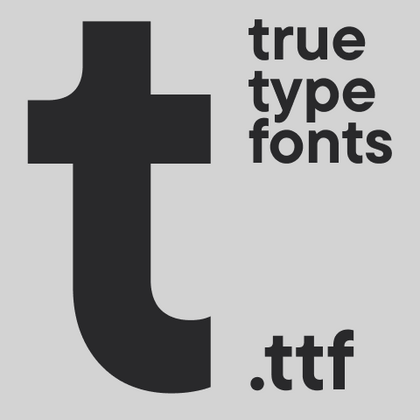
TTF шрифты
Когда нужна проверенная совместимость без сложных функций, TTF шрифты становятся идеальным решением. Каталог TypeType включает такие гарнитуры в разных стилях — от строгих рабочих вариантов до декоративных, с сохранением всех преимуществ формата: легкой установки и стабильного отображения в документах.
TT Polihaus — экспериментальный гротеск, который на первый взгляд кажется обычным, а затем разбирается на части, превращаясь в трафаретный узор.
TT Nooks Serif — акцидентная новостильная антиква с лёгким налётом эгоцентричности. У неё острый и твёрдый, при этом элегантный и статный характер.
TT Chocolates — изящный гуманистический гротеск сo сбалансированными пропорциями, близкими к классическим. Шрифт с приятным дружелюбным характером, который интуитивно воспринимается как что-то знакомое.
TT Nooks Script — шрифт с уникальным рисунком, который не имеет прямых аналогов.
TT Qurdisma — узкий и плотный декоративный шрифт, напоминающий причудливое растение. Вьющиеся, плавные контуры рождают растительный орнамент.
TT Supermolot Neue — технологичный модульный гротеск с футуристическим настроением и мощным функционалом. Яркость его характера сочетается с универсальностью применения.
TT Rationalist — функциональный и оригинальный брусковый шрифт с актуальным рисунком. Он универсален и подходит как для заголовков, так и для массивов текста.
TT Commons™ Classic — универсальный геометрический гротеск для широкого круга задач.
TT Runs — это выразительный шрифт, который идеально впишется в проекты со спортивной тематикой. При этом гарнитура отлично подойдет и для других современных проектов: после обновления сфера ее применения значительно расширилась.
TT Bells сочетает в себе элегантную мягкость антиквы с непростым и дерзким характером, который выражается в прямых срезах и клинообразных засечках. В основе шрифта лежит ширококонечное перо, характерное для старостильных шрифтов, создающее эти атмосферные срезы и засечки.
TT Severs — это геометрический гротеск с ярко выраженными элементами внутренних скруглений. Отличительной особенностью TT Severs является необычная форма внутренних овалов, которая отсылает нас к стилю традиционной арабской письменности.
TT Turns — геометрический гротеск с акцентными круглыми знаками и выразительными нависающими элементами. Это универсальный шрифт, который лаконично выглядит и отлично читается в маленьком размере, при этом в крупных кеглях становится акцидентным и проявляет свой характер на максимум. Он энергичный, сильный и динамичный — особенно отчётливо это проявляется в наклонных начертаниях.
TT Jenevers стилистически относится к голландским антиквам нового стиля. В гарнитуре присутствуют характерные детали, свойственные голландским антиквам — это ассиметричная форма засечек или нерегулярный наклон овалов.
TT Regins — шотландская новостильная антиква с королевским характером. Яркий контраст и острые треугольные засечки придают этому шрифту строгий и властный нрав.
В TT Frantz можно найти небольшие отсылки в эстетике арт-деко, которые выражены в сильно заниженной или наоборот сильно завышенной талии у букв. Кроме того, в зависимости от положения ползунка регулировки оси, у некоторых букв изменяется закрытость апертуры.
TT Quaris — изысканная и современная ленточная антиква. Перед разработкой этой гарнитуры мы провели глубокое исследование архетипов ленточных антикв.
TT Ricordi Allegria — современная ленточная антиква, отличительные особенности которой, гиперболизированная разноширинность в пропорциях, контраст между штрихами, клиновидные окончания штрихов и отсутствие традиционных засечек.